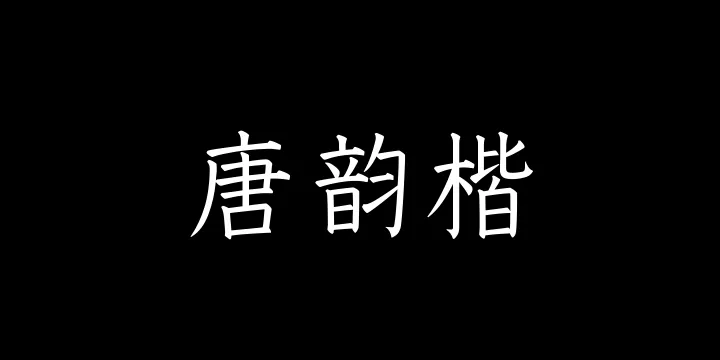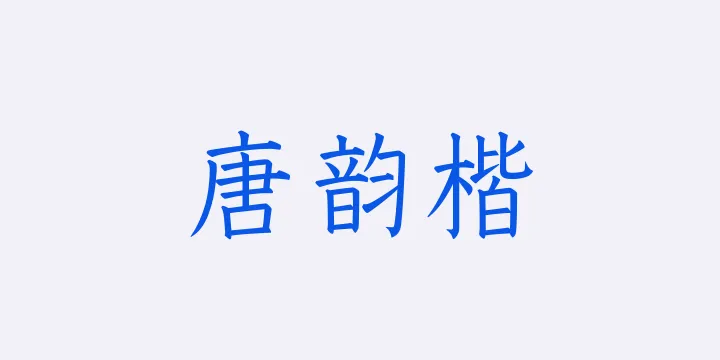
山海唐韵楷45W By 山海字库 商用字体
字体全名: 山海唐韵楷45W
字体简介: 山海唐韵楷45W,是一款全新的楷体字体,是山海唐韵楷字体家族系列中的特细款,编号45W,包含汉字9169个,符号200+个。该字体字形优美文雅,诗意内敛,取楷体细腻的书写笔画,书法的运笔走势蕴含其中,流畅自然,蕴含东方审美韵味,尽显优雅从容,秀雅清新。
所属分类: 楷体